오늘 소개해드리는 무료 폰트는 대부분 업체나 지자체에서 홍보용으로 만든 폰트인데, 상업적인 이용이 가능하니 아주 용이하게 사용하실 수 있습니다. 웹디자인이나 편집 디자인을 하실 때 적절하게 사용이 가능한 보통의 글씨체보다 두껍고 모서리가 둥글둥글한 폰트 위주로 소개 해 드리니 천천히 살펴보시고 사용해보시길 바랍니다.
1. 삼립 호빵체
삽립에서 제작 된 호빵체로, 호빵 같이 둥글도 두꺼운 느낌의 글씨체로 기본적인 검정 글씨체와 테두리가 있는 글씨체 2종류가 있으며, 영문 폰트도 마찬가지로 제대로 적용이 됩니다.
2. 레몬 빙수체
테두리 글씨체로, 라인이 상당히 두꺼워 폰트 하나하나가 마치 블록을 연상케 하고 영문 폰트도 두껍기 때문에 귀여운 연출이 가능한 폰트입니다.
3. 엄마 까투리체
안동시의 지역 캐릭터를 홍보하기 위해 제작된 폰트로, 두껍고 옹골차지만 귀여운 느낌이 강한 폰트입니다.
4. 상상토끼 꽃길체
두꺼운 손글씨 느낌의 폰트로 자유롭고 거친 느낌이 있습니다. 용도에 따라 고급스러운 느낌과 귀여운 느낌을 동시에 줄 수 있어 다양하게 쓸 수 있습니다.
5. 빙그레 싸만코체
붕어싸만코 아이스크림에 적혀있는 폰트로, 부드럽고 귀여운 느낌을 주며 둥글둥글해 시각적으로 편안함을 줄 수 있습니다.
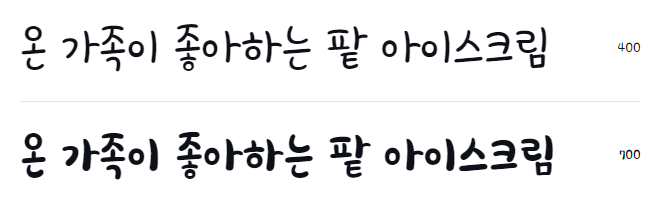
6. 넥슨 배찌체
넥슨의 게임 카트라이더 캐릭터인 배찌를 모티브로 제작 된 폰트입니다. 라인이 엄청 두껍지도 않고 얇지도 않은 적당한 두께이며 일정하게 유지 됩니다. 손글씨에서 살짝 두꺼워진 느낌으로 보시면 될 것 같고, 부담스럽지 않고 무난하게 사용이 가능할 것 같습니다.
7. 쿠키런 폰트
게임 쿠키런에서 제작 된 각진 느낌의 폰트입니다. 안동 엄마 까투리체와 비슷한 느낌이지만 조금 더 딱딱한 느낌으로, 제목에 어울리는 폰트라서 가족성이 좋습니다.
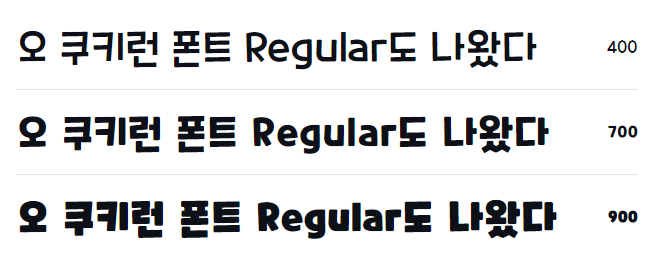
8. 망고빙수체
레몬 빙수체를 제작한 디자이너 분이 제작하신 또 다른 폰트로, 각이 딱딱 떨어지는 절제된 늒미과 라운딩 된 귀여운 느낌이 공존하는 폰트로, 영문 폰트에도 꽤나 잘 어울립니다.